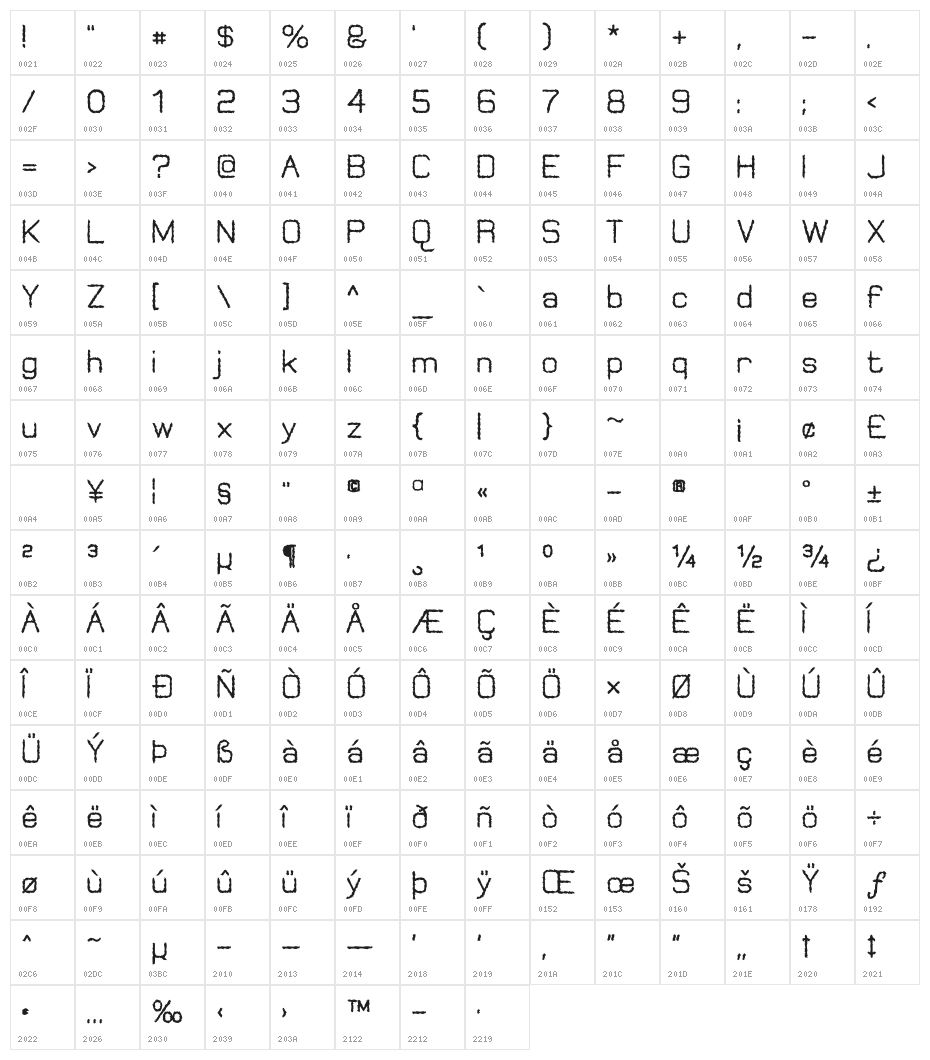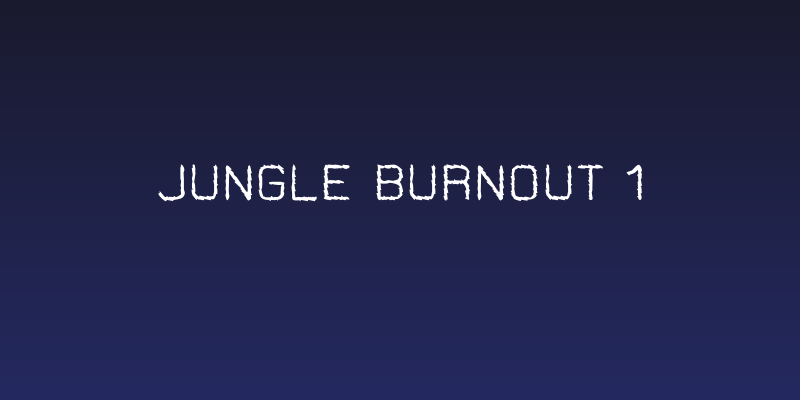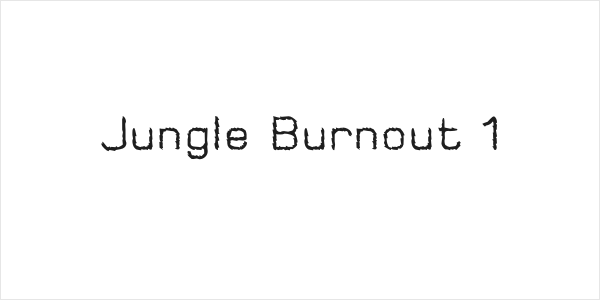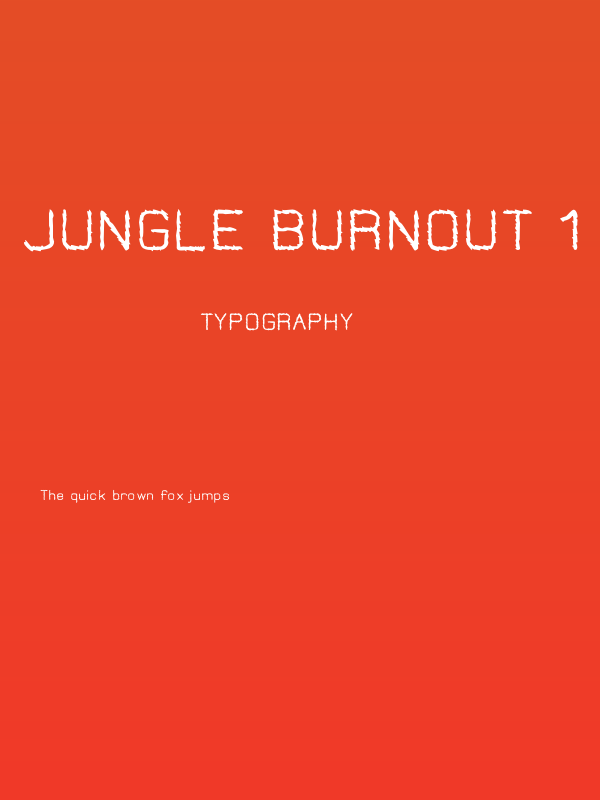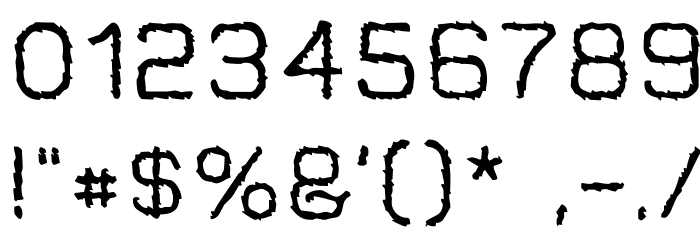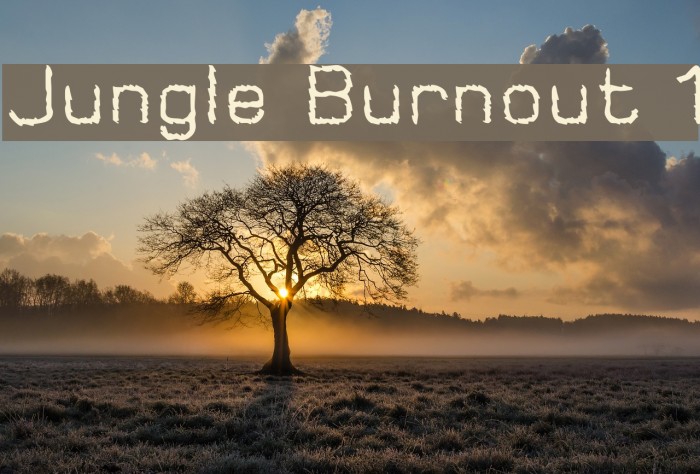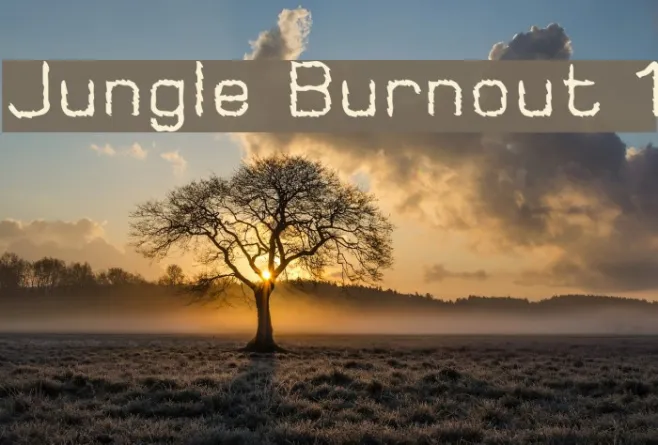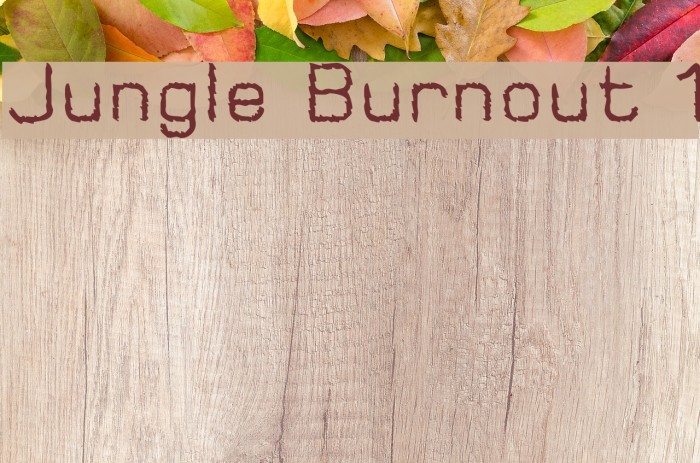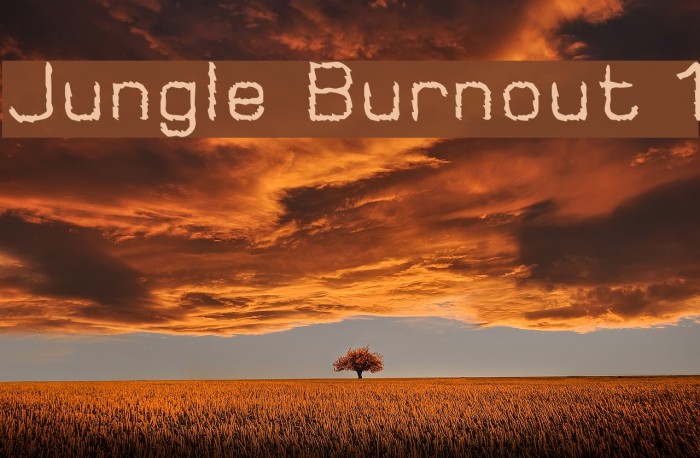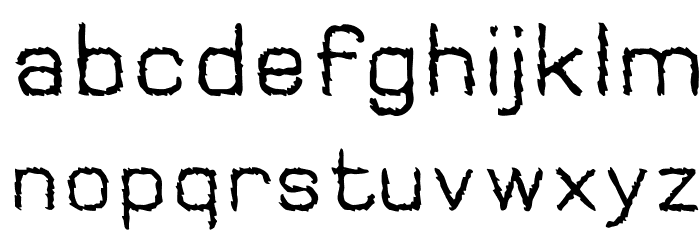
Jungle Burnout 1 Font
| Progetti proposti | Ideal for outdoor-themed posters, adventure branding, rustic packaging, and artistic projects that require a natural, rugged look. |
Jungle Burnout 1